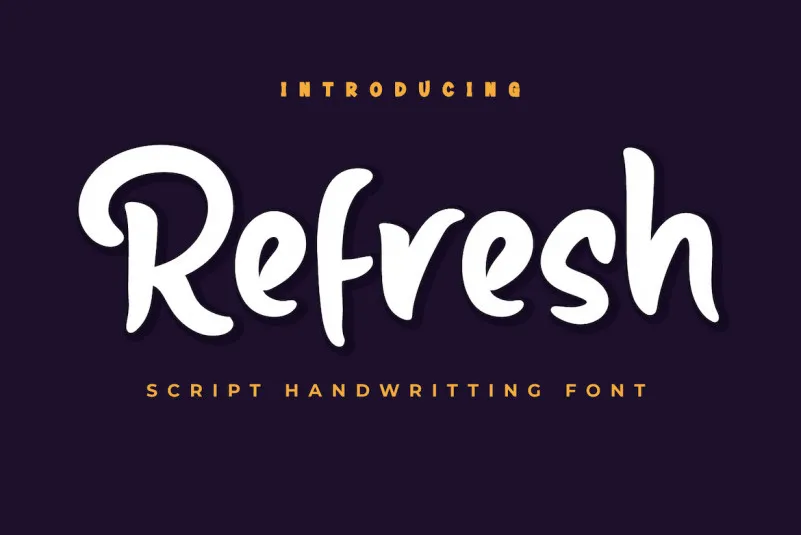
A Refresh Font é uma elegante seleção para projetos que exigem uma pausa rápida, seja ela uma introdução à sua newsletter especial ou o texto principal de seu site personalizado. Inspirada na sensação suave e delicada de um toque manual, esta fonte traz um ar sofisticado ao design de texto e cabeçalhos para projetos especiais. Seja você um designer que busca uma pausa entre as tarefas diárias ou alguém que valoriza a qualidade visual em sua página web, a Refresh Font oferece precisão e elegância. Perfeita tanto para textos como para elementos destacados do seu design, essa fonte é uma escolha ideal para aqueles que procuram um equilíbrio entre beleza e funcionalidade. Aproveite esta oportunidade de dar um toque especial a seus projetos com Refresh Font.